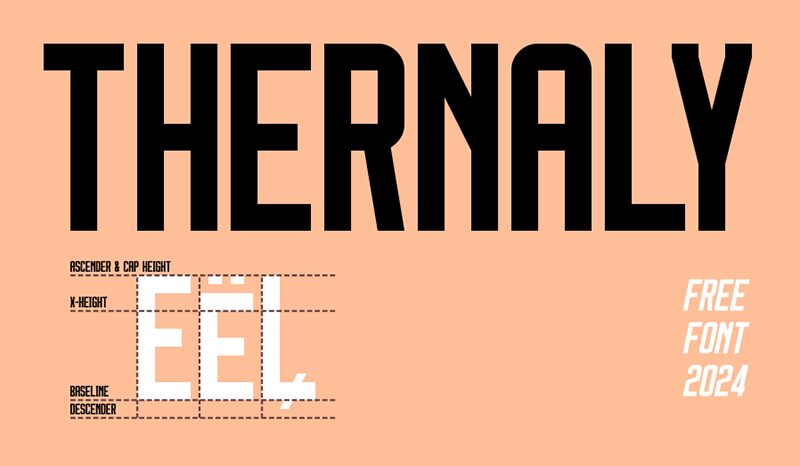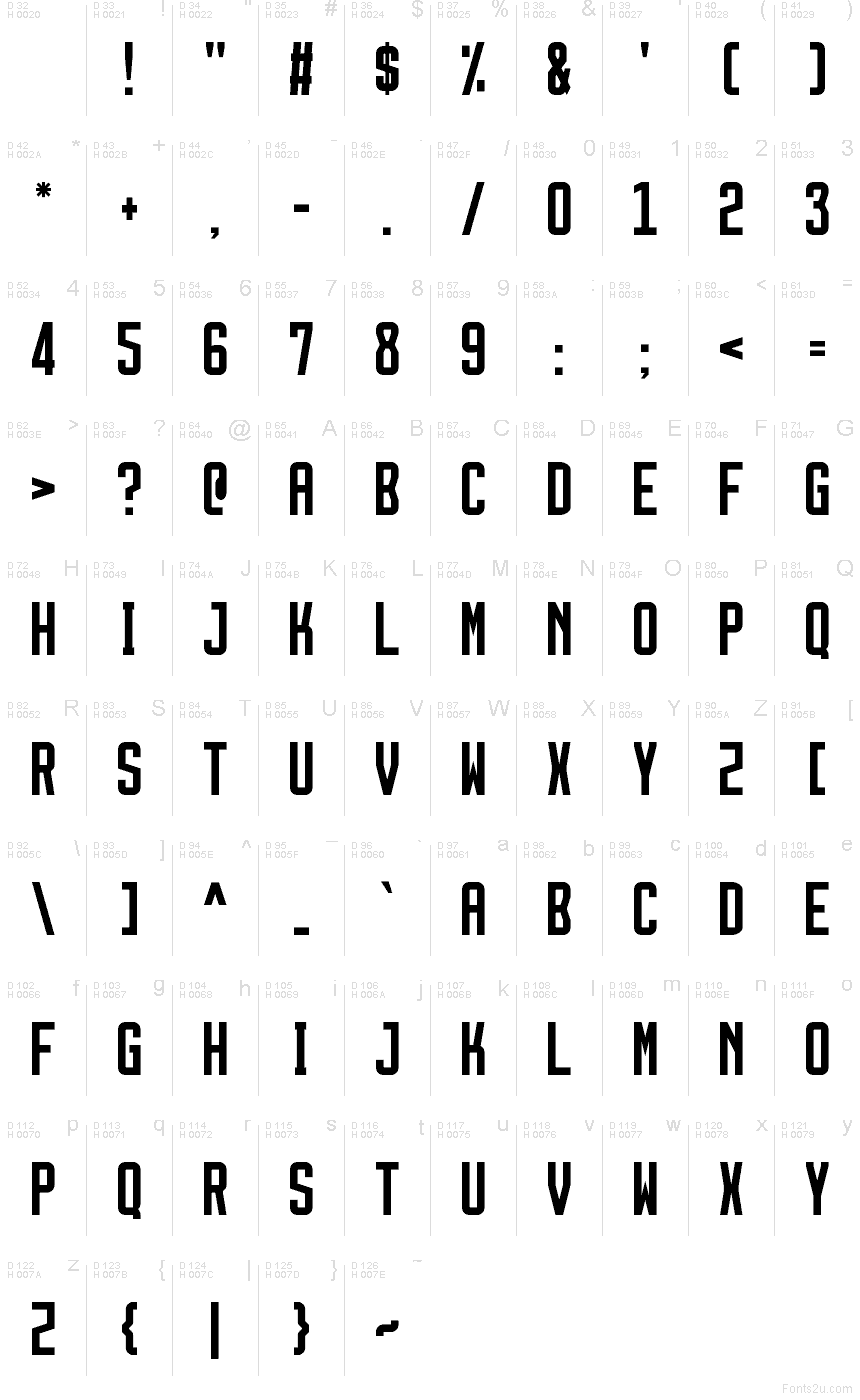
Thernaly od GGBotNet je bezplatné, zúžené bezpatkové písmo s vysokými, úzkými znaky, rovnými stranami a hranatými rohy, které mu dodávají ostrý, kompaktní rytmus. Jednoduchá konstrukce udržuje těsné rozestupy a konzistentní geometrii v celé sadě, přičemž písmo vyniká otevřenými vnitřními tvary bez zbytečných dekorací.
Thernaly skvěle funguje v titulcích plakátů, letácích na akce, sportovní grafice, logotypu, obalech i krátkých redakčních popiscích, protože jeho zúžená struktura šetří místo a přitom působí výrazně graficky. Toto bezplatné písmo se hodí také na bannery, obaly alb a webovou grafiku, kde je potřeba silný vertikální akcent bez ornamentálních detailů.